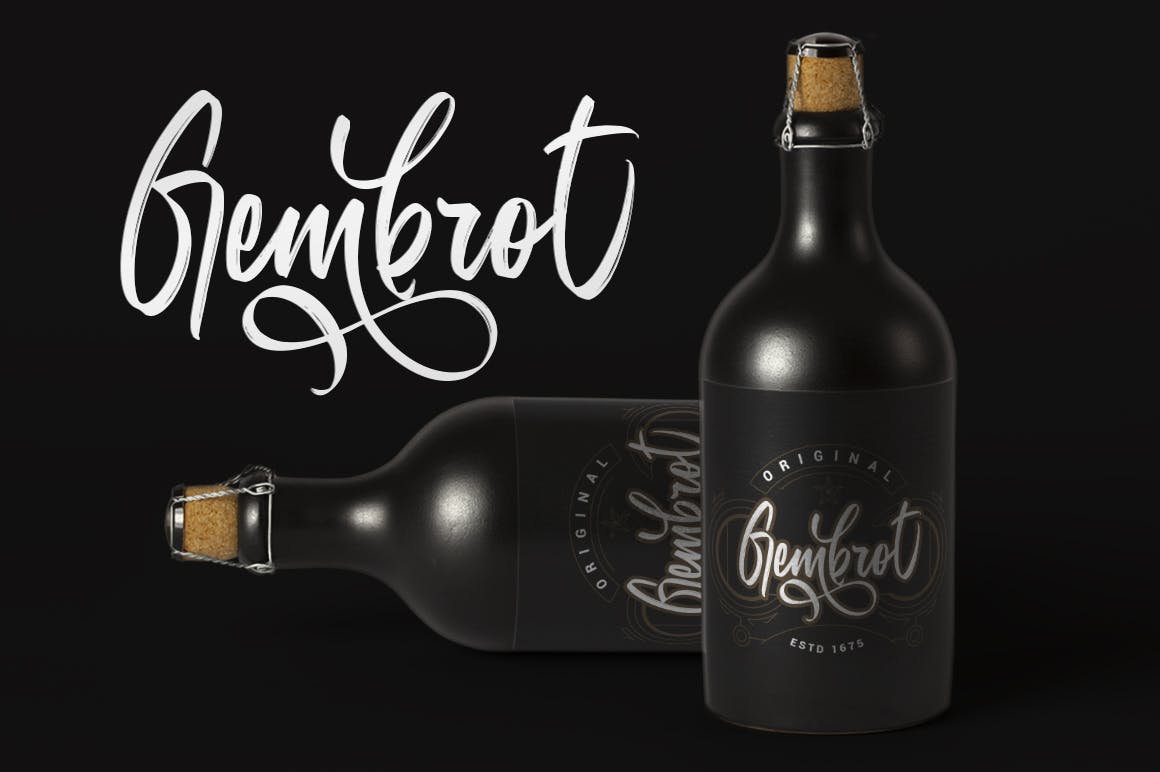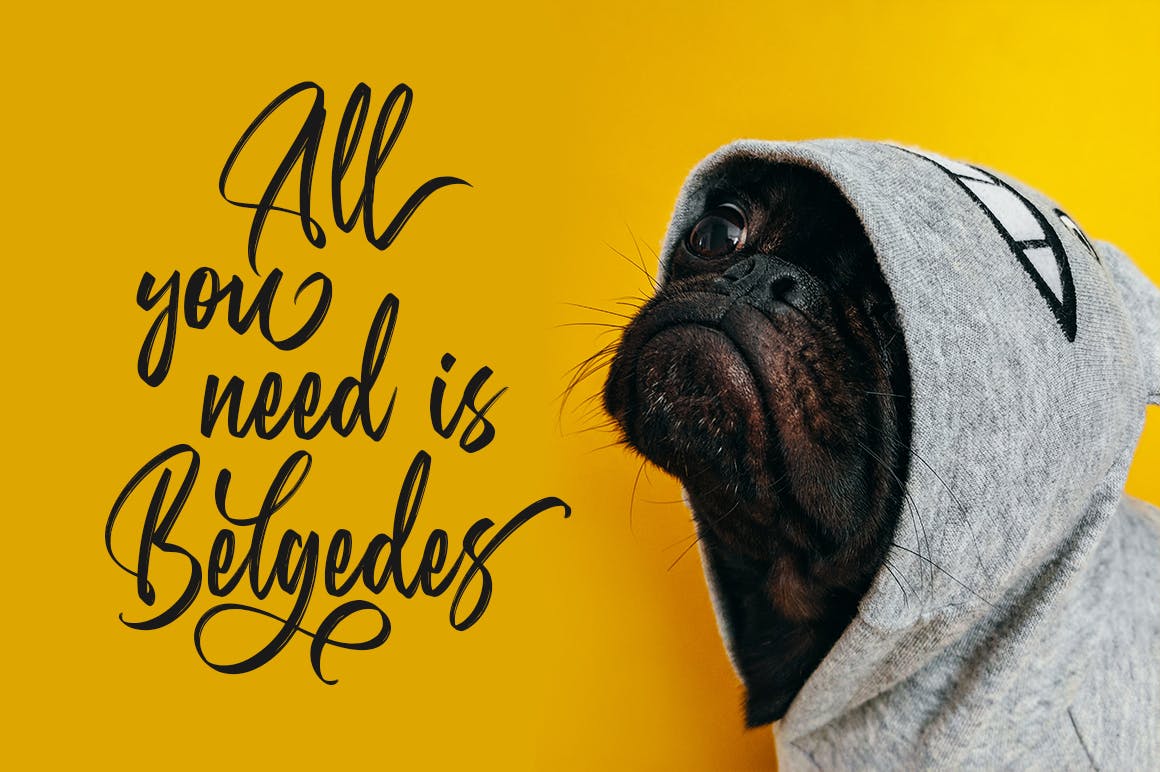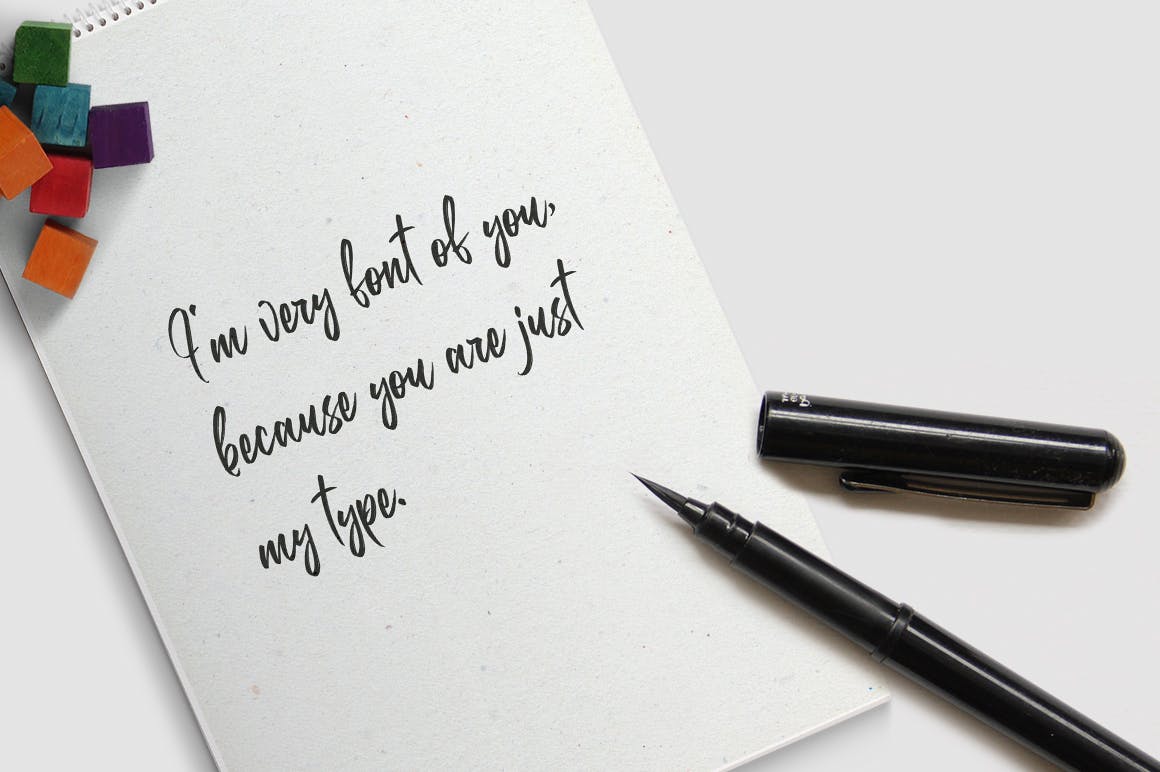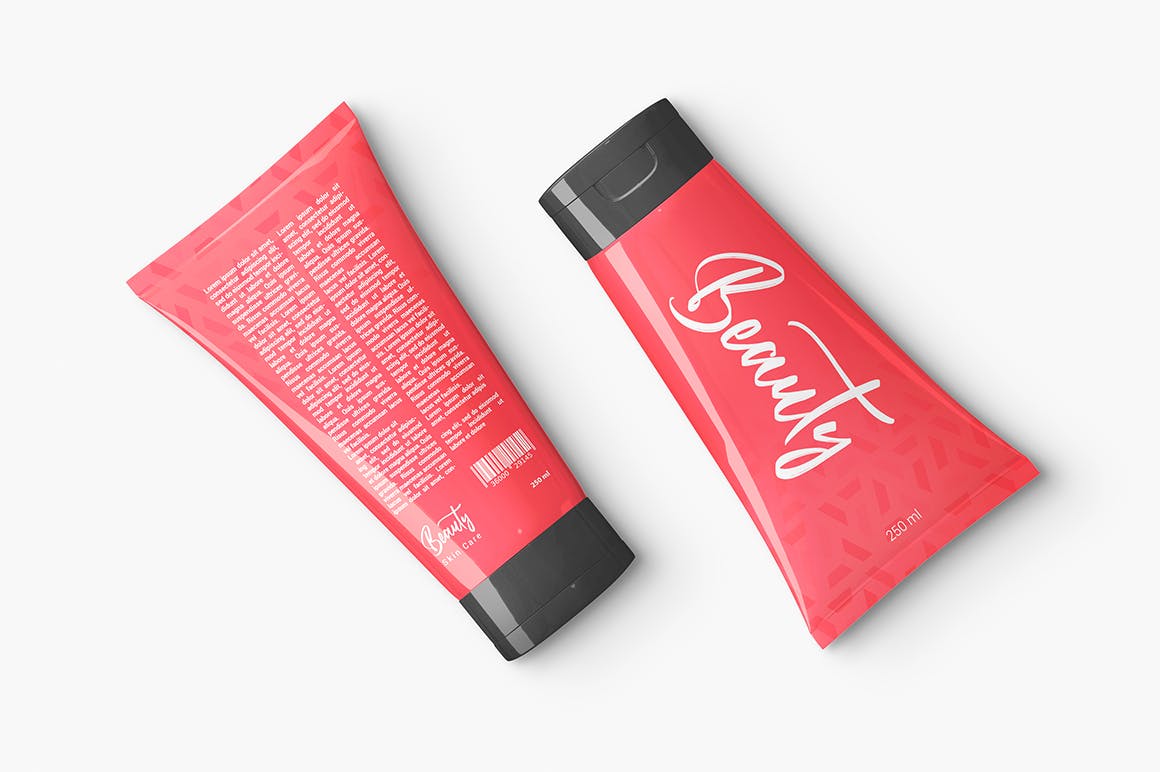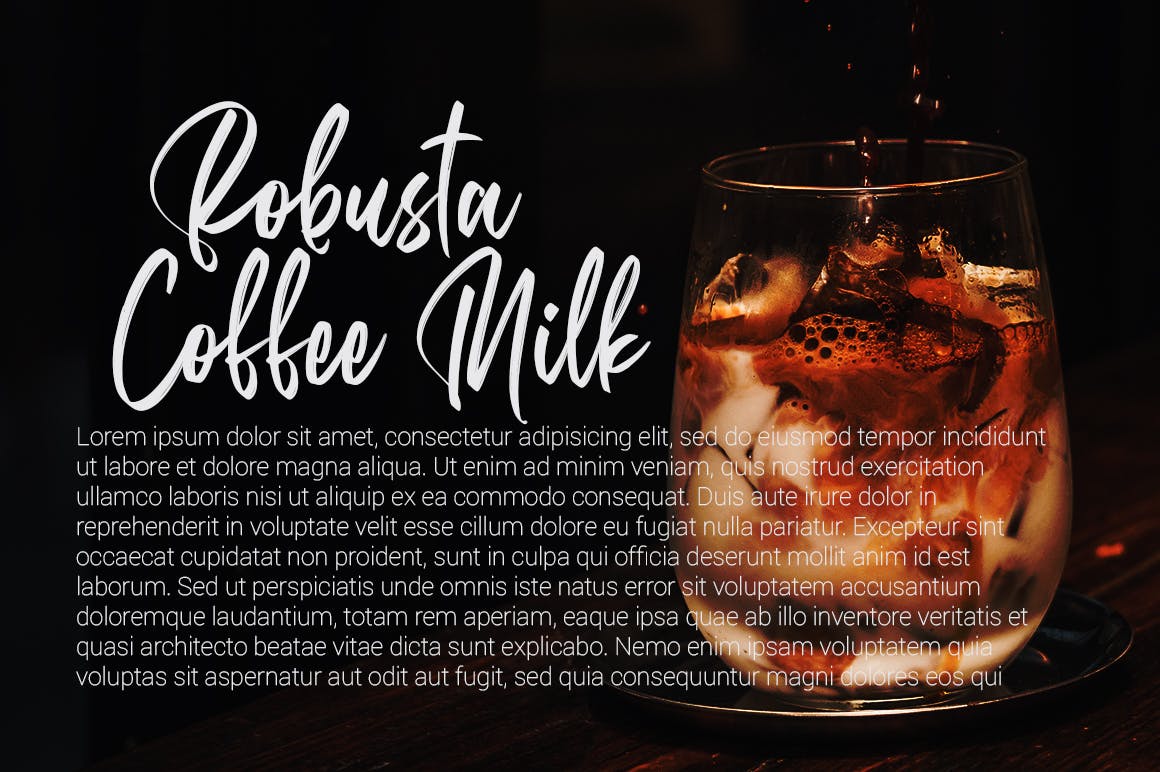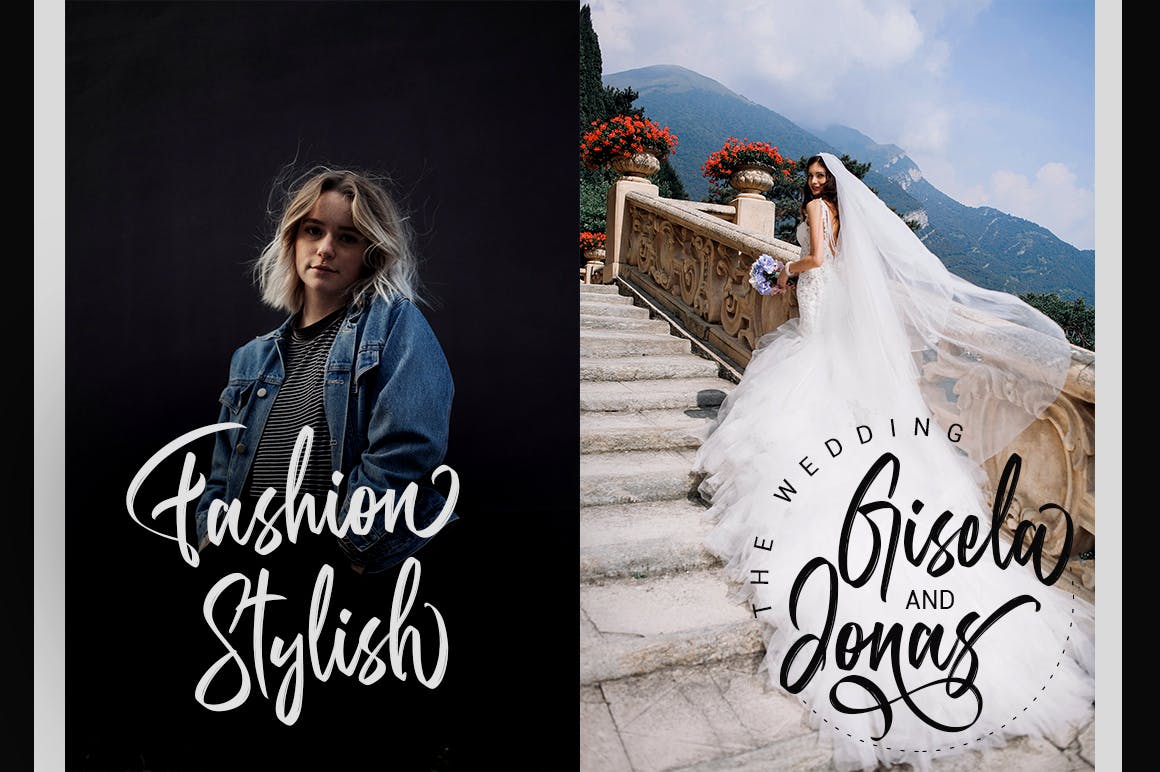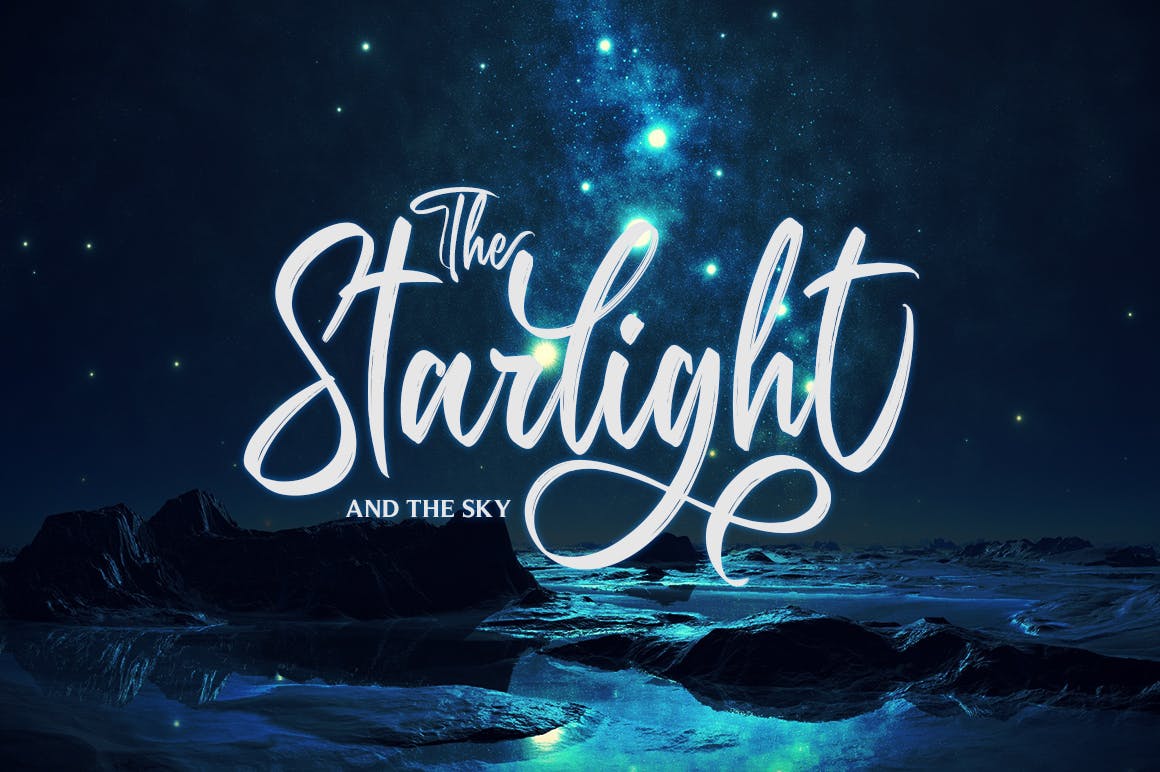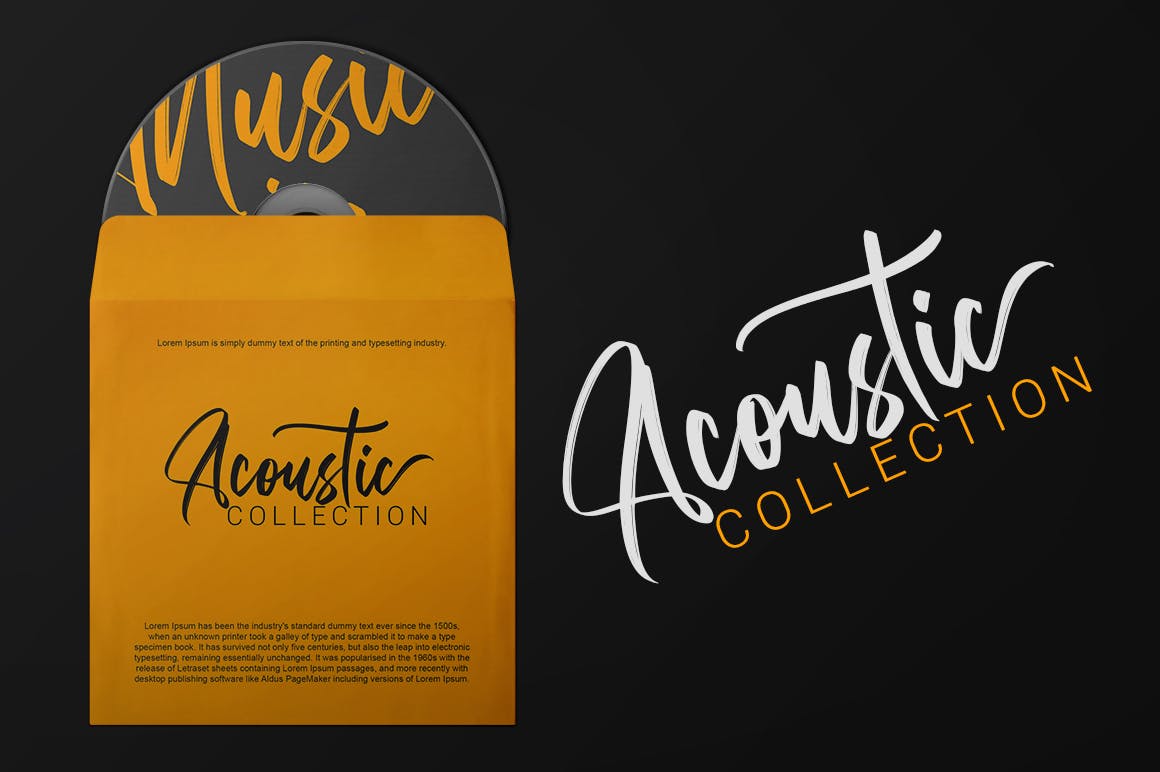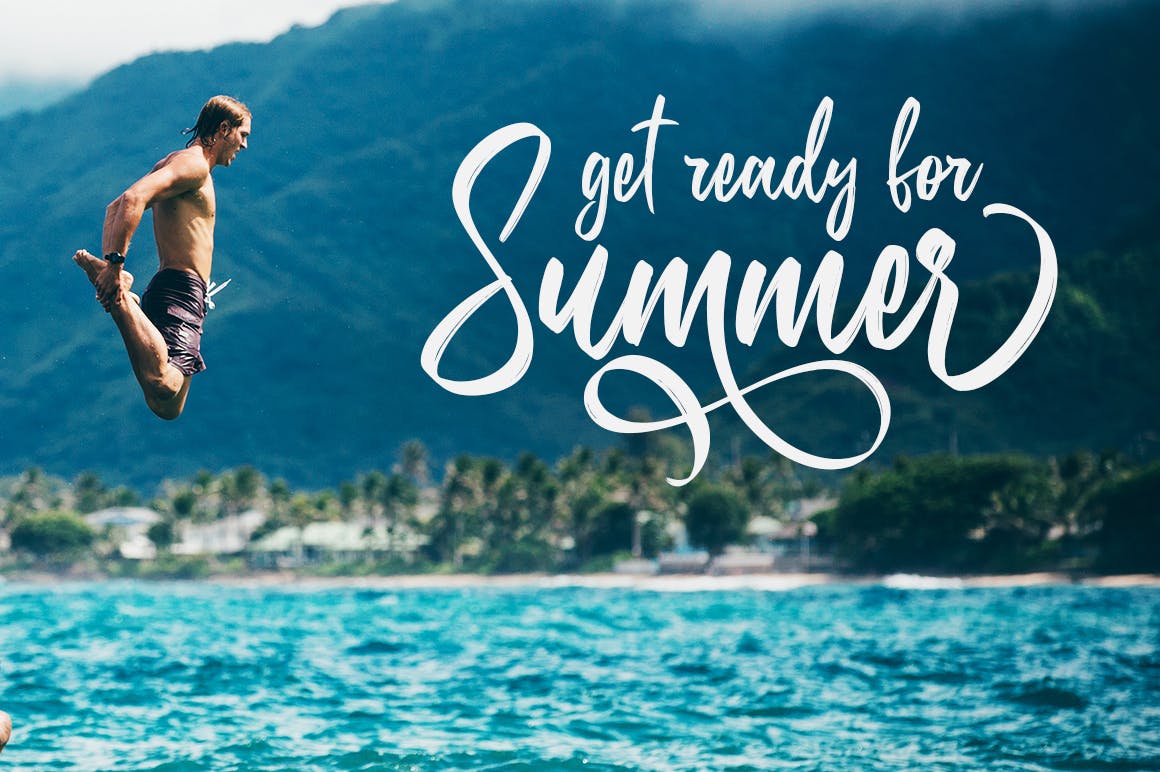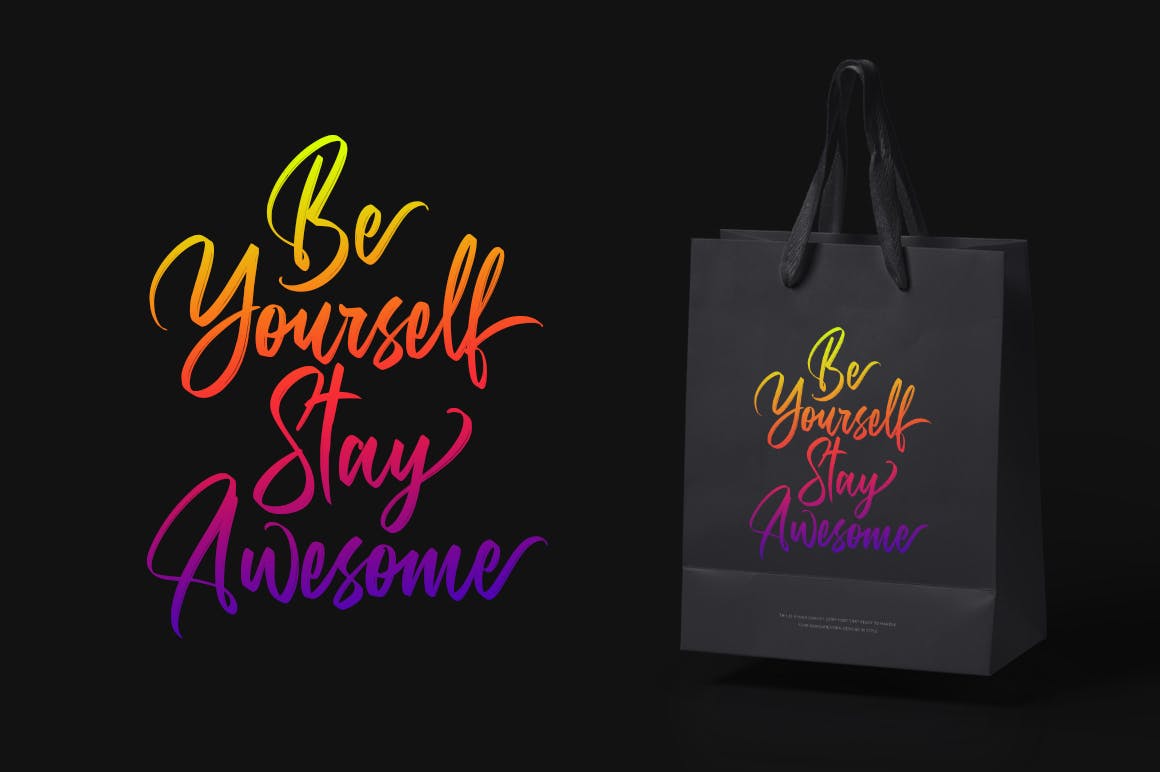
فونت Belgedes یک فونت خوشنویسی با سبک دستنویس است. این فونت در هر طراحی ظاهری فوقالعاده دارد و به شدت برای لوگو، پوستر، برندینگ، نقل قولها یا هر چیزی که نیاز به لمسهای از ظرافت دارد، توصیه میشود. فونت Belgedes دارای تعدادی لیگاتور و مجموعهای کامل از کاراکترهای جایگزین است که میتوانید به تمام این جایگزینها از طریق پنل Open Type در نرمافزار طراحی خود دسترسی پیدا کنید.